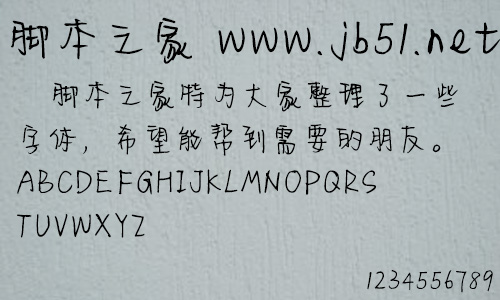
一只麋鹿體由神韻字庫(kù)出品的藝術(shù)字體,字體筆觸粗細(xì)適中,書寫灑脫,具有很好的視覺(jué)感,適合應(yīng)用于藝術(shù)設(shè)計(jì)、平面宣傳設(shè)計(jì)、網(wǎng)頁(yè)設(shè)計(jì),書法字帖等領(lǐng)域。有需要的朋友快來(lái)下載使用吧!